Typography không chỉ là việc chọn một font chữ đẹp, mà còn là nghệ thuật tối ưu khoảng cách giữa các dòng, ký tự và từ ngữ để văn bản trở nên cân đối và dễ đọc. Trong bài viết này, chúng ta sẽ khám phá Kerning, Leading và Tracking – 3 yếu tố quyết định sự thành công của bất kỳ thiết kế văn bản nào. Hãy cùng tìm hiểu cách sử dụng chúng để tạo ra những tác phẩm typography đỉnh cao!
Kerning – Khoảng cách giữa 2 ký tự
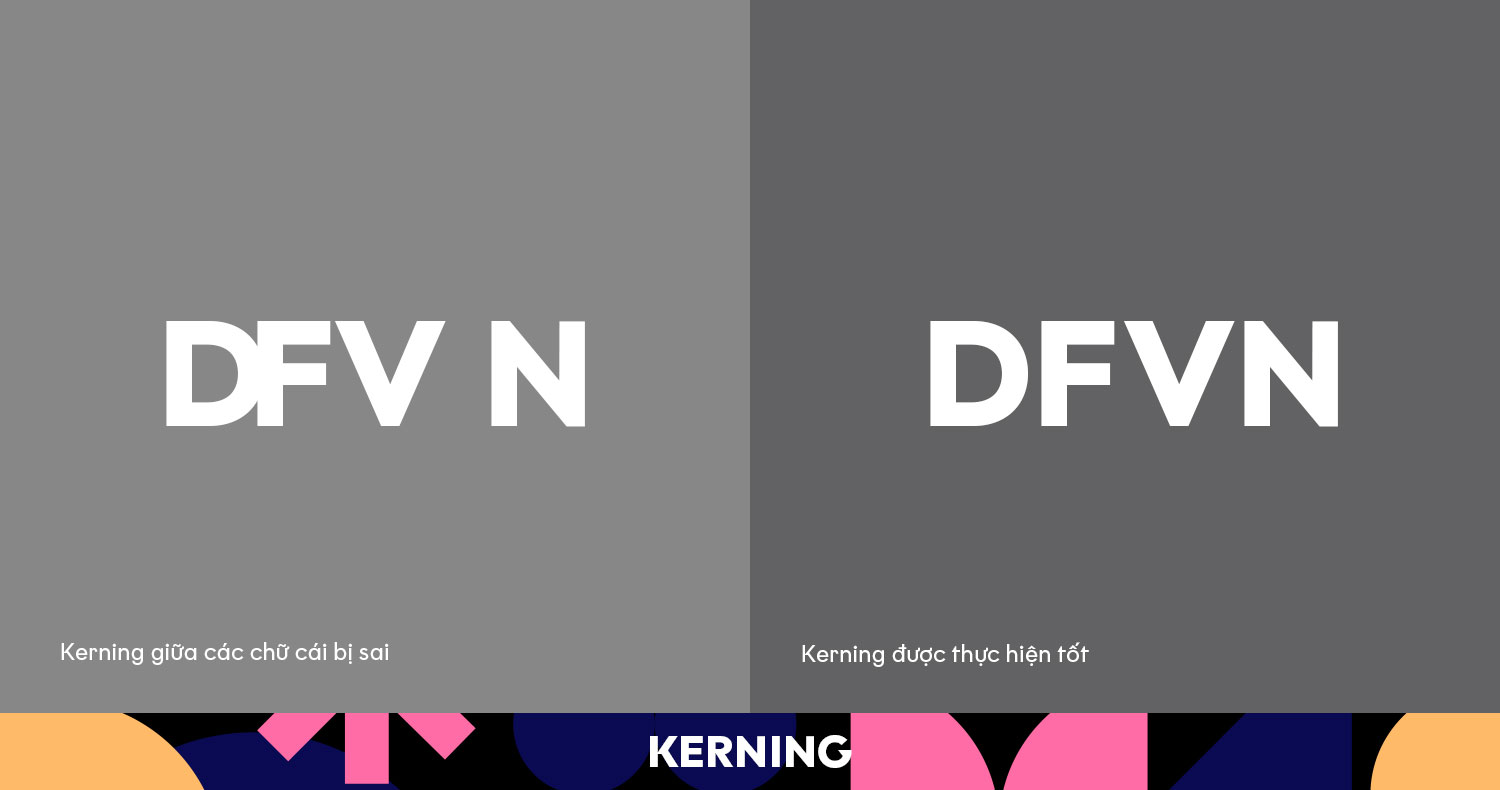
Kerning là việc điều chỉnh khoảng cách giữa hai ký tự trong văn bản để tạo sự cân đối và dễ đọc. Nếu các ký tự quá sát hoặc quá xa nhau, văn bản sẽ trở nên khó chịu với mắt người đọc.
Khi nào cần kerning?
Đối với nội dung văn bản dài (body text), việc điều chỉnh kerning thủ công không cần thiết vì các khoảng cách thường rất nhỏ và không đáng chú ý. Tuy nhiên, với những nội dung hiển thị lớn như logo, bảng hiệu, poster, kerning là điều bắt buộc.
Những lỗi thường gặp với kerning
- Khoảng cách quá hẹp: Khi các ký tự “dính chặt” vào nhau, từ ngữ trở nên khó đọc, rối mắt.
- Khoảng cách quá xa: Nếu các ký tự bị tách biệt, người đọc dễ mất tập trung.
Làm thế nào để điều chỉnh kerning tốt nhất?
Quan sát kỹ: Kerning đòi hỏi con mắt tinh tường để nhận ra sự bất hợp lý trong khoảng cách. Bạn có thể thực hành và luyện tập để kerning font chữ một cách chính xác.
Cách điều chỉnh Kerning trong Photoshop và Illustrator: Sử dụng phím tắt trong Photoshop và Illustrator, đặt con trỏ giữa hai ký tự cần chỉnh, giữ Alt/Option và dùng phím mũi tên để điều chỉnh khoảng cách.
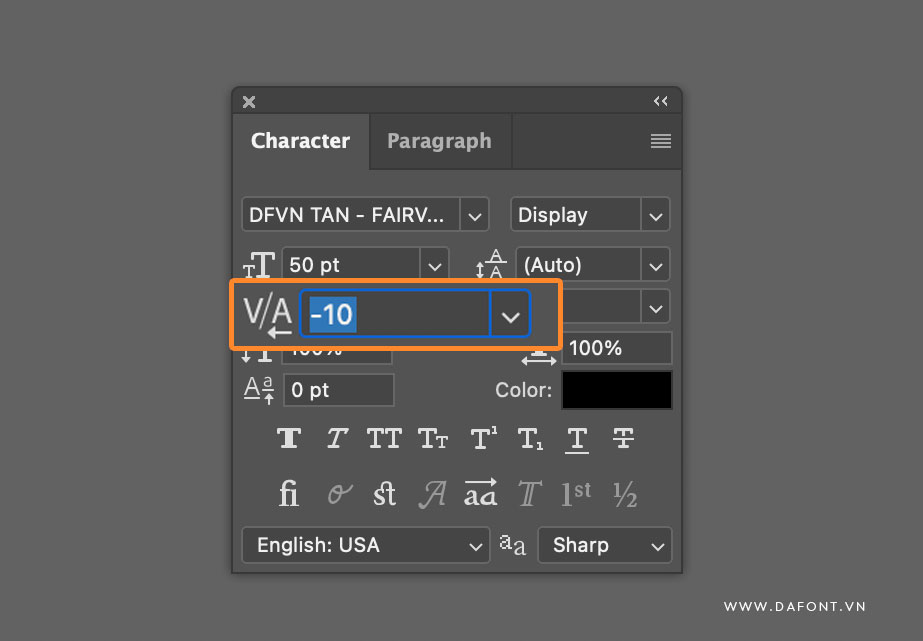
Kerning là một kỹ năng quan trọng trong typography, giúp bạn kiểm soát từng chi tiết nhỏ nhất để tạo ra những thiết kế ấn tượng và chuyên nghiệp. Hãy nhớ rằng, trong typography, sự khác biệt giữa “tốt” và “tuyệt vời” nằm ở những chi tiết nhỏ như kerning.
Mẹo thực hành
Bạn có thể luyện tập khả năng kerning qua các trò chơi trực tuyến như KernType, giúp bạn rèn luyện mắt nhìn tinh tế hơn.
Leading – Khoảng cách giữa các dòng chữ
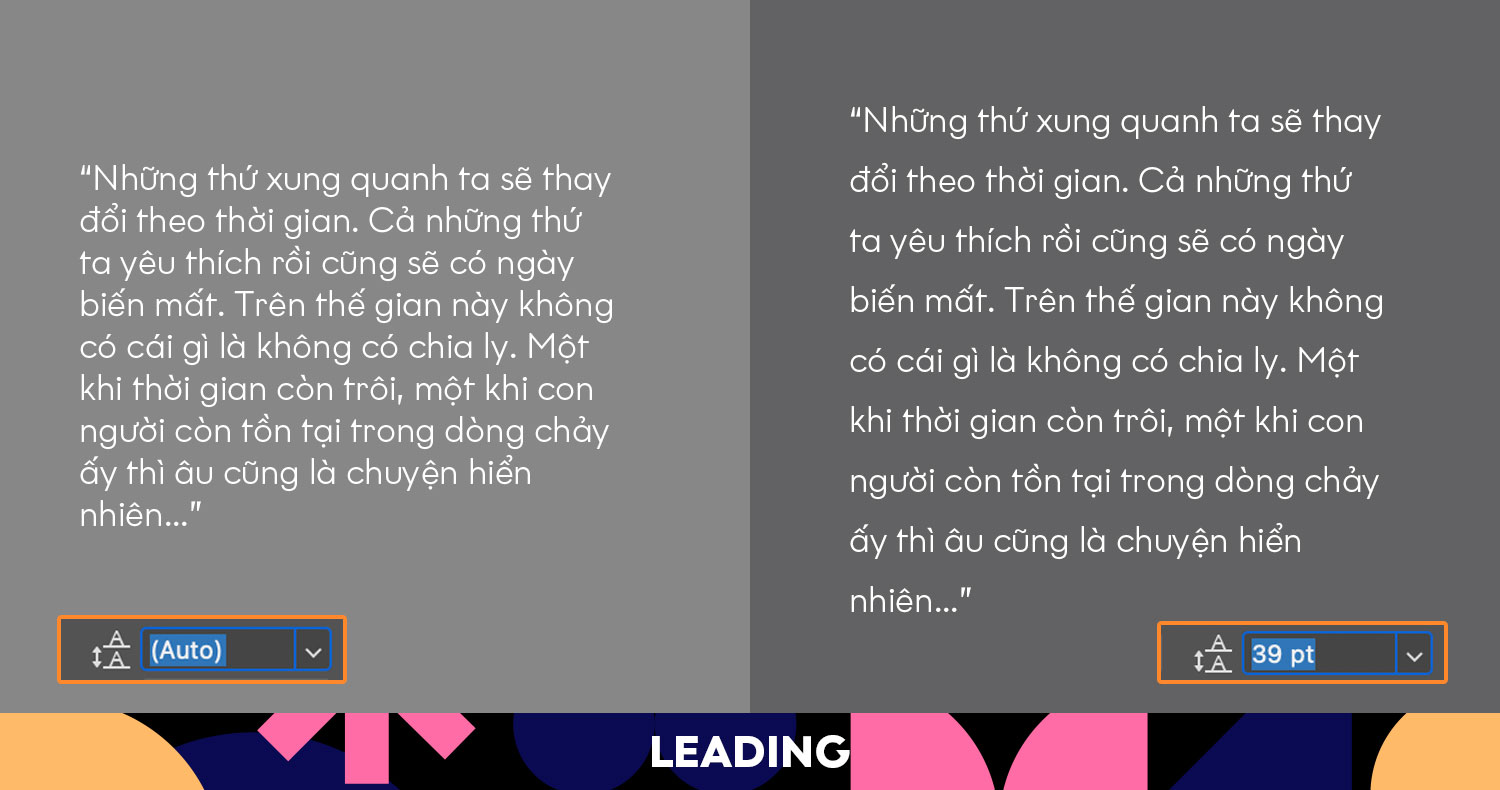
Leading (hay khoảng cách dòng) là khoảng cách từ đường cơ sở (baseline) của một dòng chữ đến đường cơ sở của dòng kế tiếp. Nó ảnh hưởng đến cách các dòng văn bản tương tác với nhau và quyết định không gian tổng thể mà đoạn văn chiếm trong thiết kế. Leading chuẩn có thể giúp văn bản trông cân đối, dễ đọc và thu hút hơn, trong khi leading không phù hợp có thể khiến văn bản trở nên bí bách hoặc rời rạc.
Tại sao leading quan trọng?
- Tăng khả năng đọc: Leading quá hẹp khiến văn bản trông chật chội, gây khó chịu khi đọc. Ngược lại, leading quá rộng có thể làm mất đi tính liền mạch.
- Tạo sự cân đối: Leading giúp tạo ra sự hài hòa giữa các dòng văn bản, đặc biệt quan trọng trong các thiết kế phức tạp với nhiều đoạn văn hoặc khi kết hợp nhiều loại font chữ.
- Tính thẩm mỹ: Leading phù hợp giúp văn bản trông gọn gàng, chuyên nghiệp, đặc biệt trong các bài thuyết trình, thiết kế website hay bài in ấn.
Cách điều chỉnh leading hiệu quả
Quy tắc chung: Leading nên lớn hơn kích thước font khoảng 20%. Ví dụ, với font 12pt, leading hợp lý là khoảng 14pt. Tuy nhiên, con số này có thể thay đổi tùy thuộc vào loại font, nội dung và mục đích sử dụng.
Cách điều chỉnh leading trong phần mềm: Trong Photoshop hoặc Illustrator, bạn có thể thay đổi giá trị leading trong bảng Character. Hãy thử nghiệm để tìm khoảng cách phù hợp nhất với kiểu chữ và ngữ cảnh thiết kế.
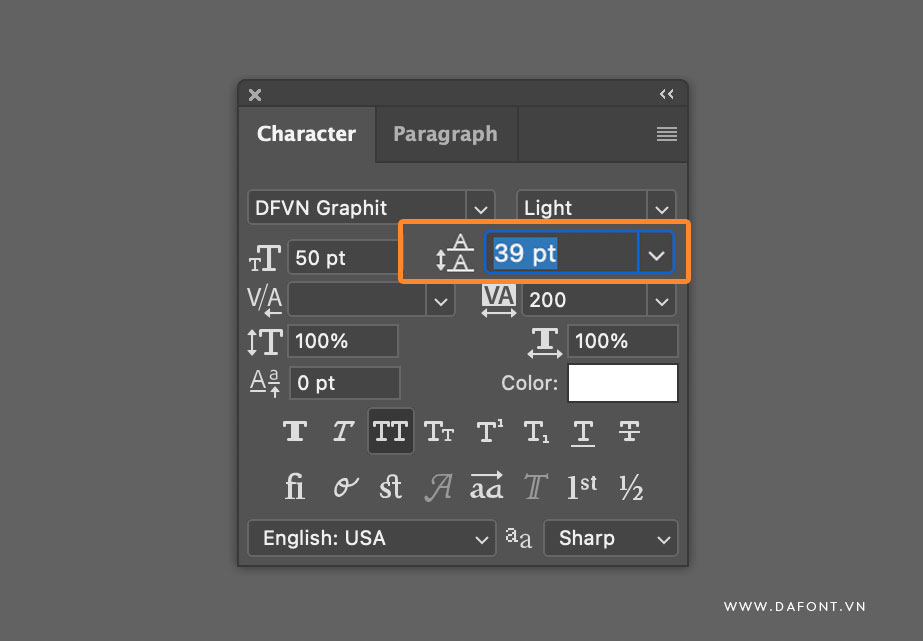
Tracking – Khoảng cách giữa toàn bộ ký tự
Khác với kerning, vốn tập trung vào khoảng cách giữa hai ký tự cụ thể, tracking điều chỉnh khoảng cách giữa tất cả các ký tự trong một từ, câu, hoặc đoạn văn bản một cách đồng đều. Điều này giúp tạo nên sự thống nhất trong thiết kế và cải thiện trải nghiệm đọc.
Ứng dụng của tracking
- Tăng tính thẩm mỹ: Tracking giúp văn bản trở nên thoáng đãng hơn hoặc phù hợp với không gian thiết kế.
- Chữ in hoa: Đặc biệt hữu ích khi làm việc với chữ in hoa toàn bộ (all-caps), nơi các ký tự thường cần thêm không gian để trông cân đối hơn.
- Tạo điểm nhấn: Một từ được mở rộng tracking có thể tạo cảm giác quan trọng và nổi bật hơn.
Cẩn thận với tracking
- Không lạm dụng: Tracking quá lớn sẽ khiến văn bản khó đọc, còn quá nhỏ làm chữ trông ngột ngạt.
- Thử nghiệm: Điều chỉnh tracking vừa phải để phù hợp với ngữ cảnh thiết kế, đặc biệt là trên các màn hình nhỏ.
- Chú ý font chữ: Mỗi font có đặc điểm riêng, do đó cần điều chỉnh tracking phù hợp với từng loại font để đạt được hiệu quả tối ưu.
Cách điều chỉnh tracking
Trong Photoshop và Illustrator, bạn chỉ cần chọn văn bản, mở bảng Character, và thay đổi giá trị tracking (nằm dưới trường kerning).
Kết luận
Kerning, Leading và Tracking là 3 yếu tố không thể thiếu để tạo nên một thiết kế văn bản đẹp mắt và chuyên nghiệp. Khi nắm vững cách sử dụng chúng, bạn sẽ không chỉ cải thiện thẩm mỹ mà còn nâng cao trải nghiệm của người đọc. Hãy thử áp dụng những bí quyết trên và biến typography của bạn thành một tác phẩm nghệ thuật thực thụ!